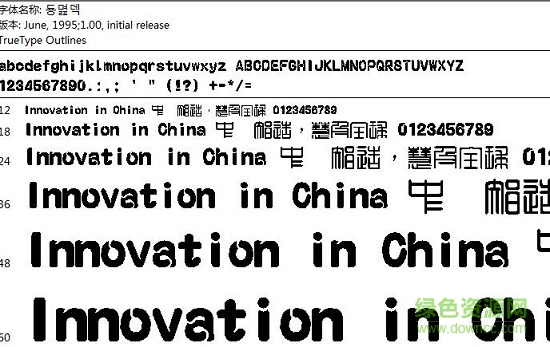
富漢通粗印篆體繁是一款由篆書書法制作而來的藝術(shù)字體,這款字特意加粗了筆畫,使得每個(gè)字都會顯得格外的鮮明,整體效果也十分的醒目,有需要的朋友歡迎下載!
富漢通粗印篆體繁是富漢通字體中的一款特色鮮明的篆體字體,是根據(jù)古書法演變而來,完美的繼承了篆體應(yīng)有的本質(zhì)特色,字形方正,筆畫優(yōu)美!